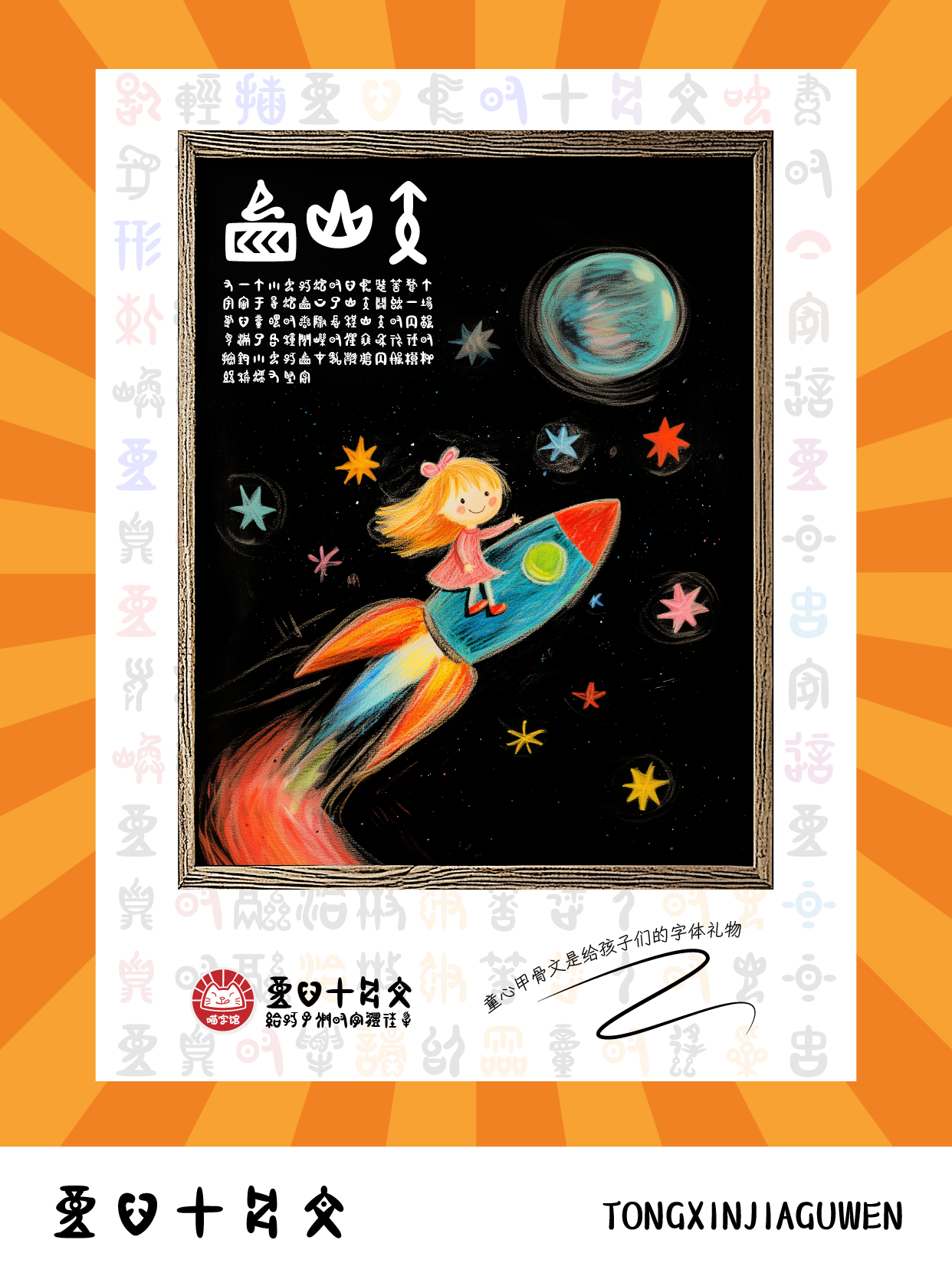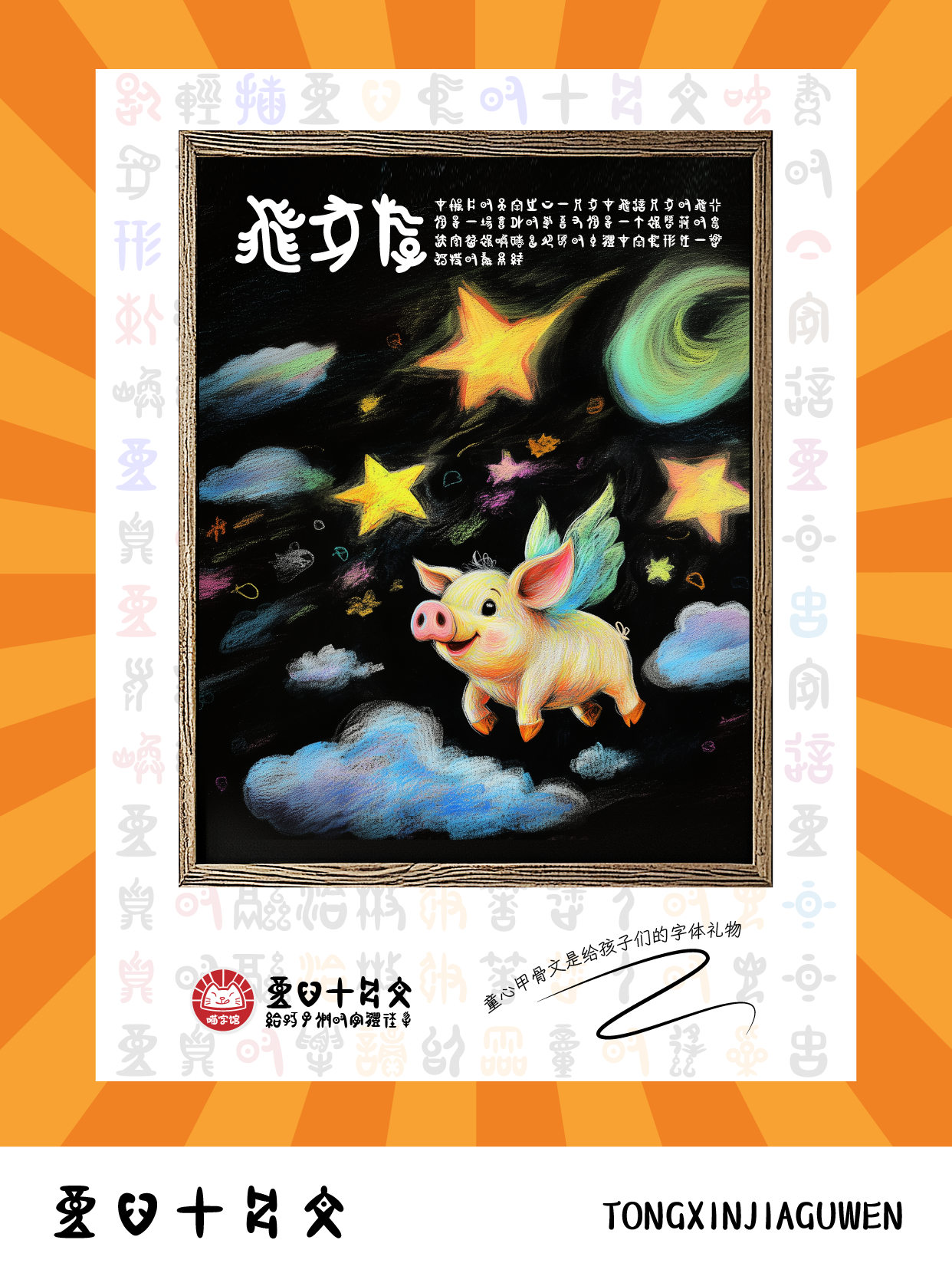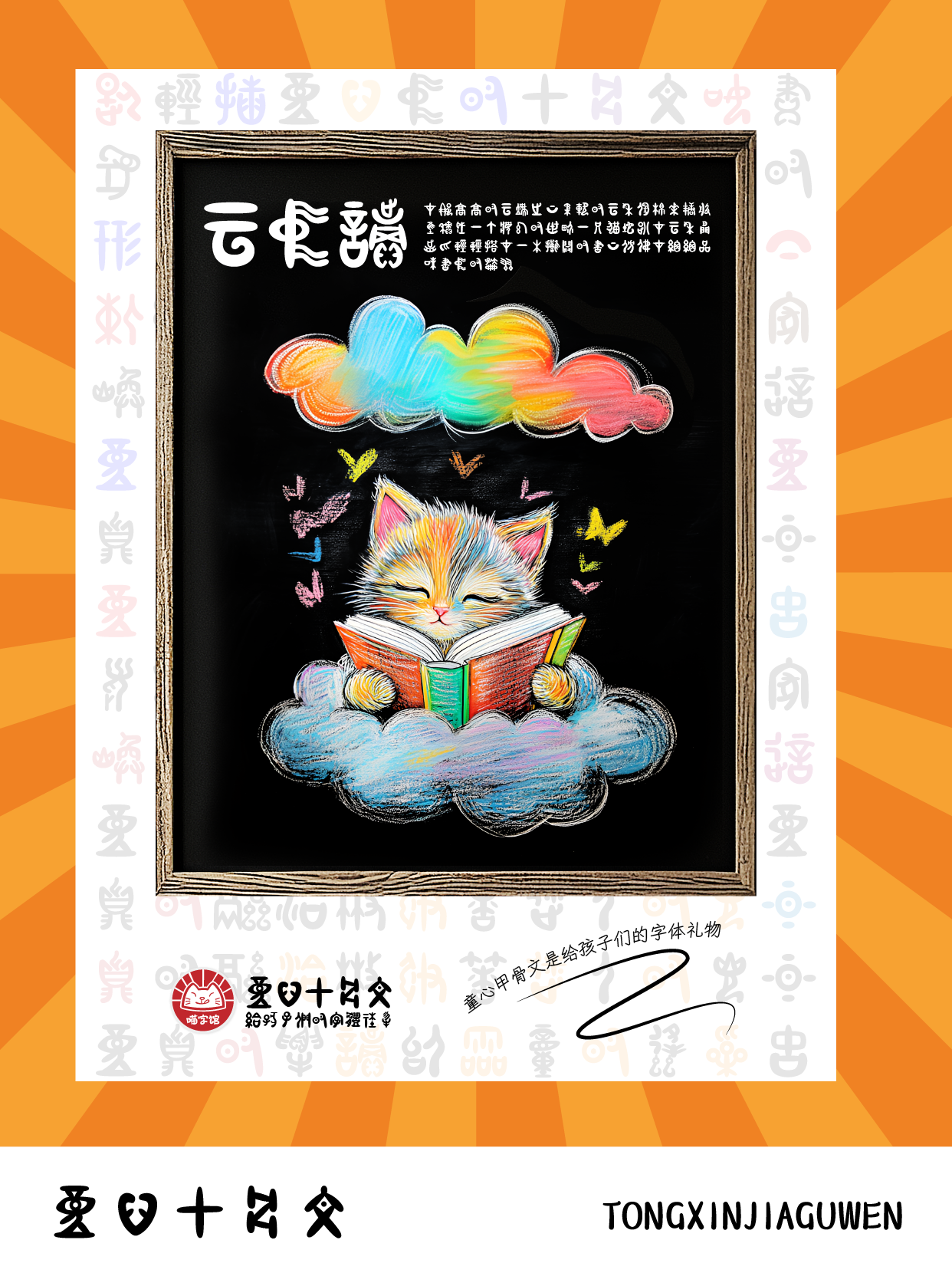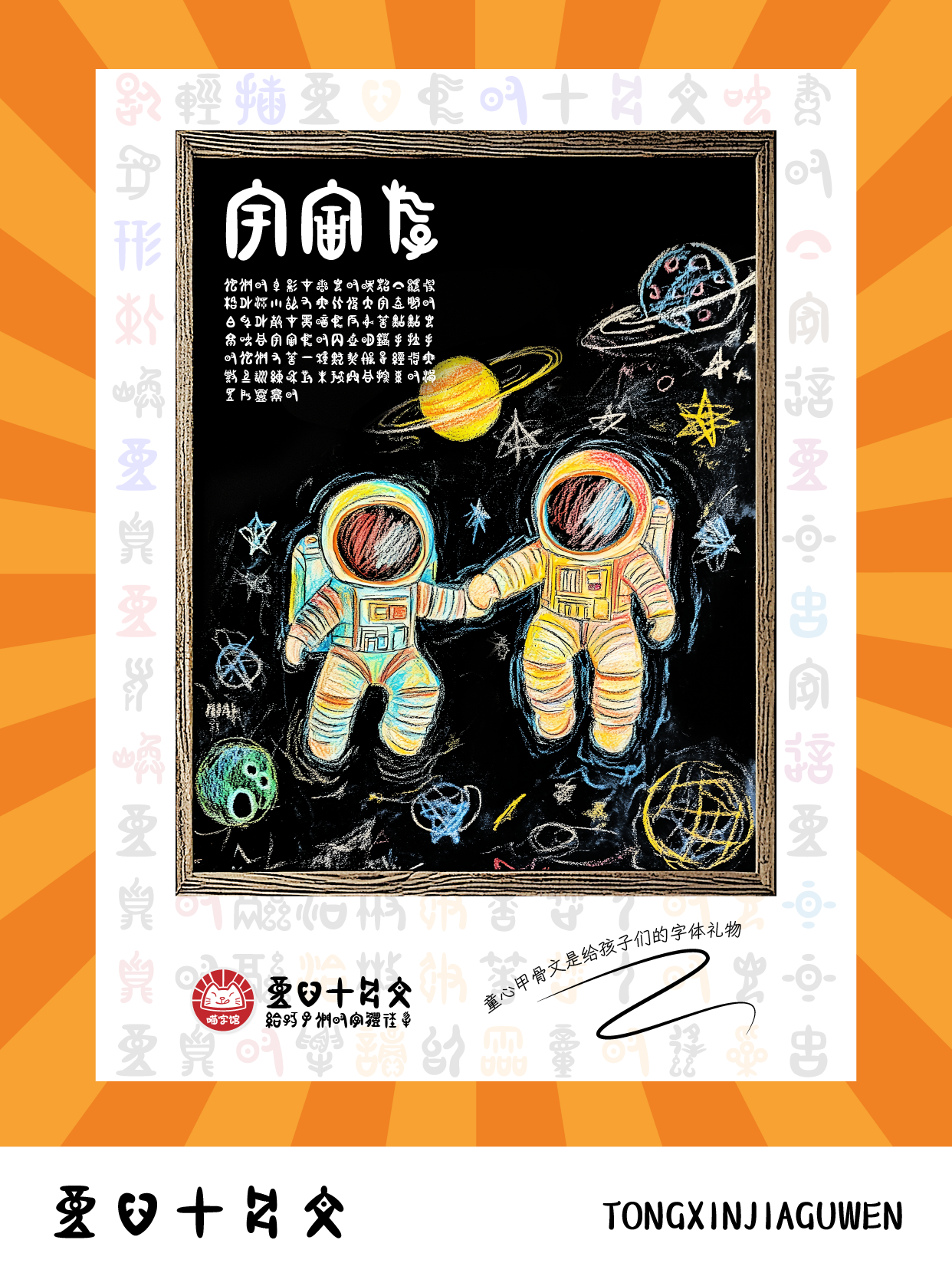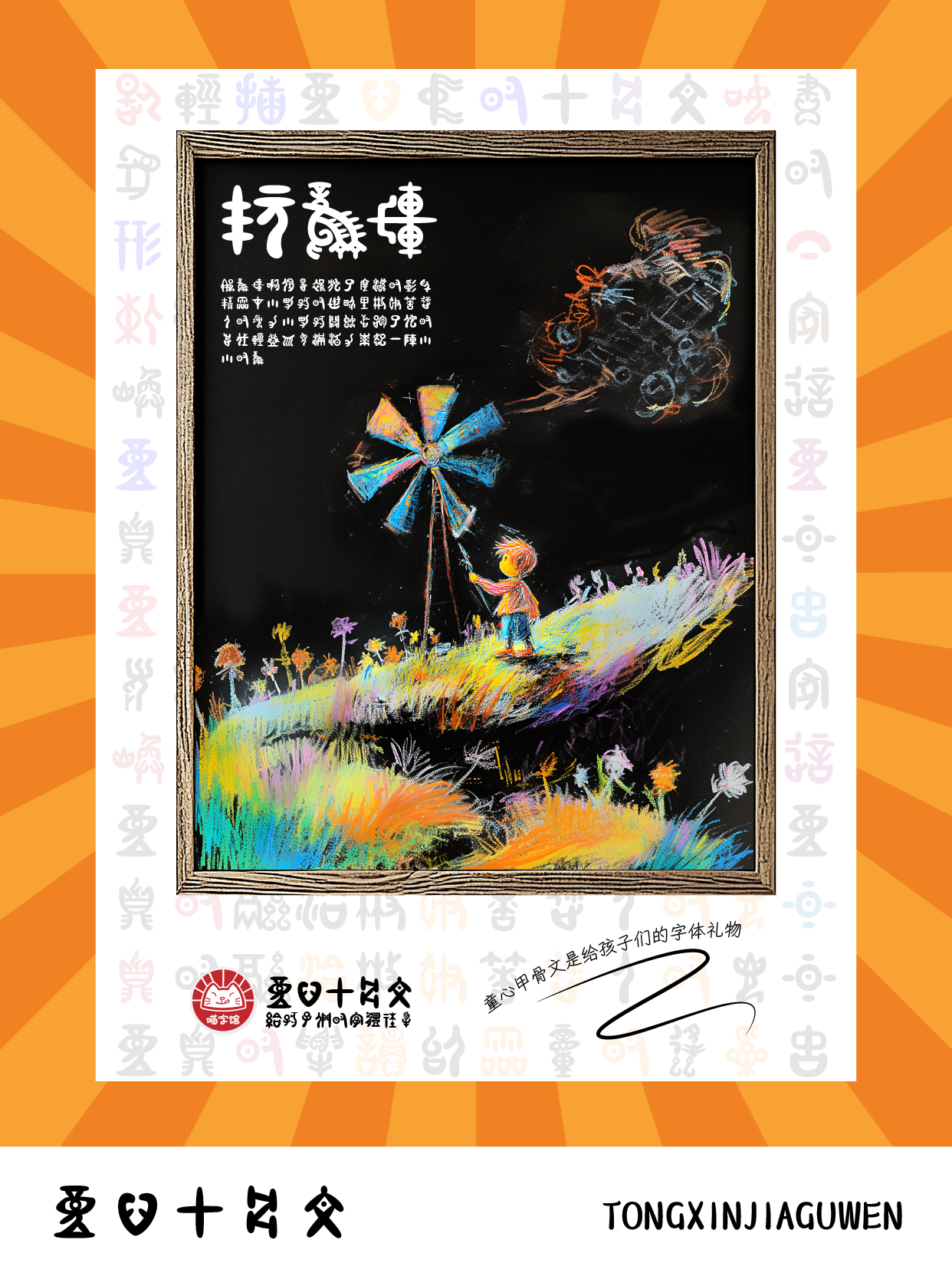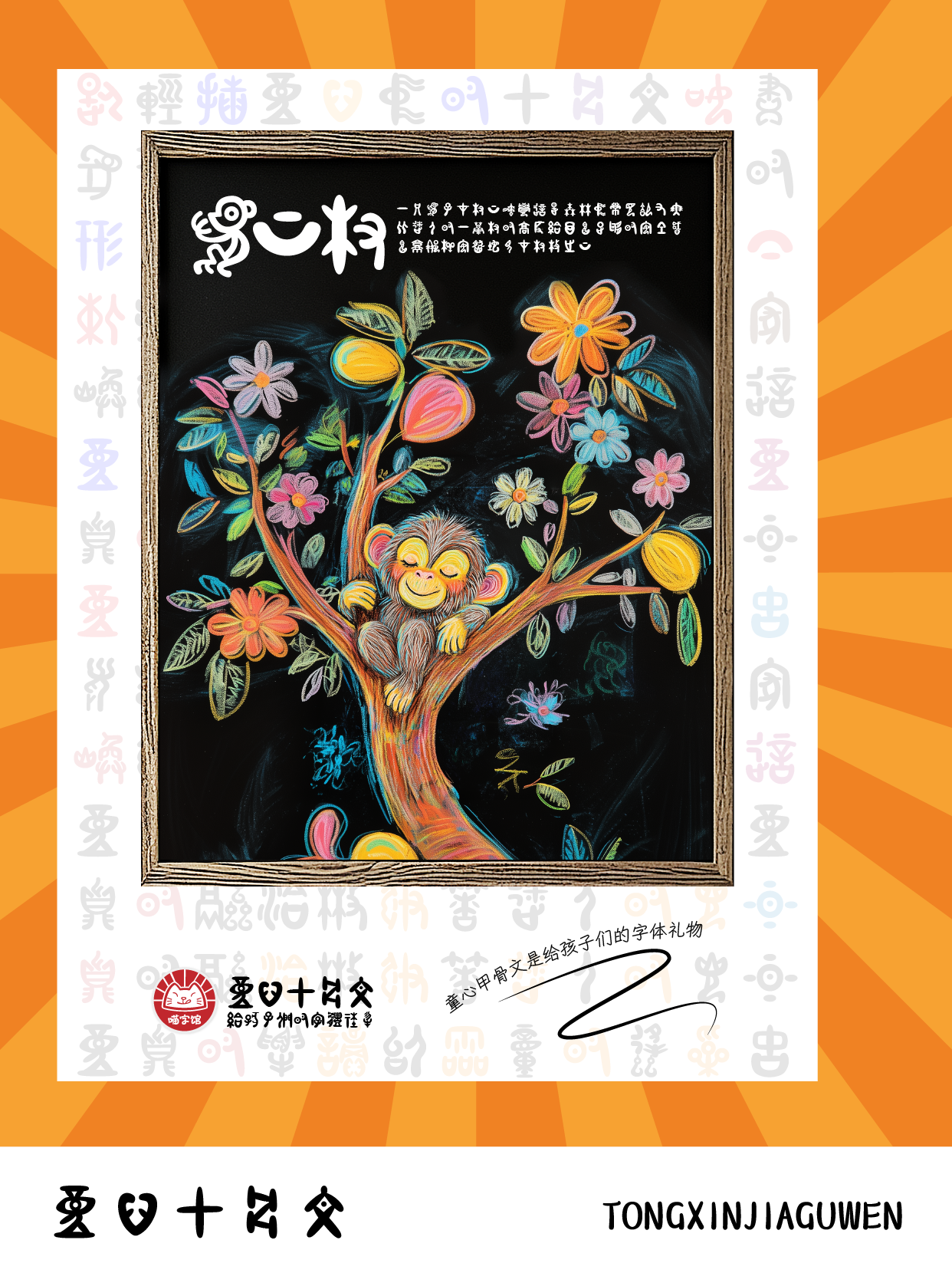
童心甲骨文
TongXinJiaGuWen
古老而神秘的文字
童心甲骨文是一款定位于儿童教育行业的细分字库产品。它的整体风格轻盈、圆润,带有强烈的手写感和卡通特点。这些特点使得它非常适合用于教育相关的素材和物料。它的设计风格适合吸引孩子们的注意力,让他们更加乐于参与学习和探索。此外,童心甲骨文的字形清晰可辨,便于儿童初学者识字和书写。无论是在教室、教材、海报还是其他教育资源中使用,童心甲骨文都能为儿童教育增添趣味和活力。